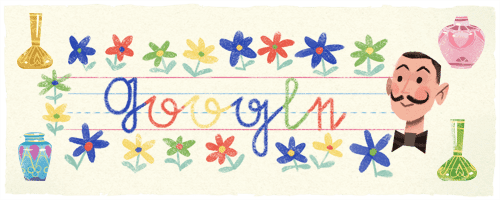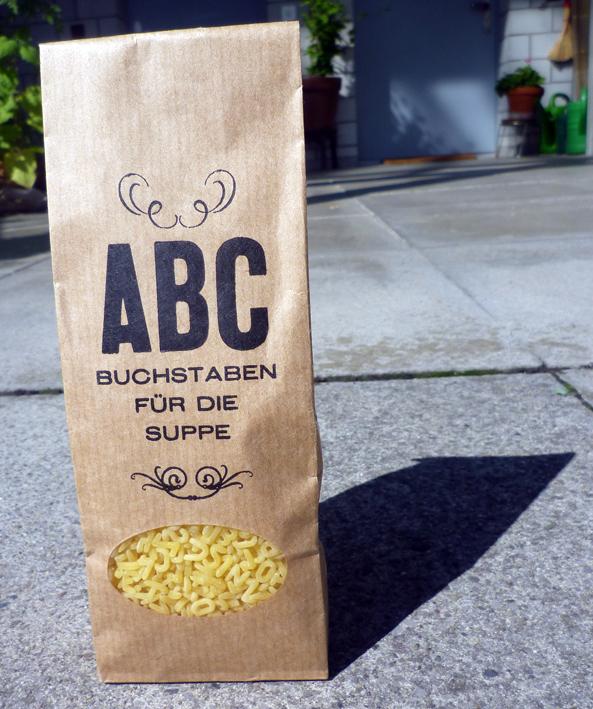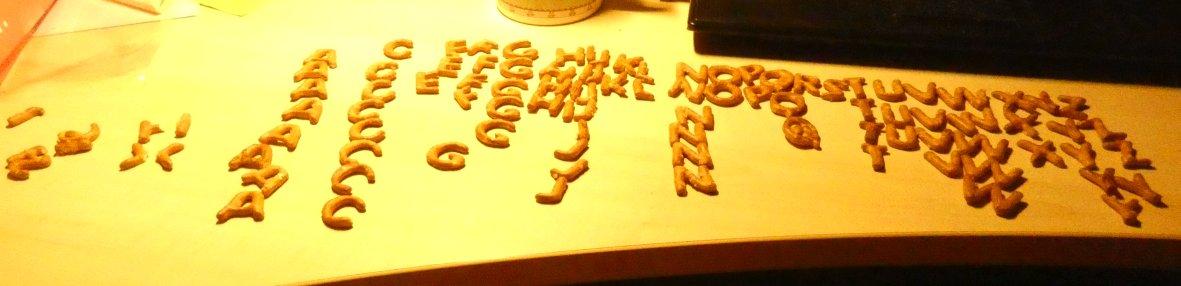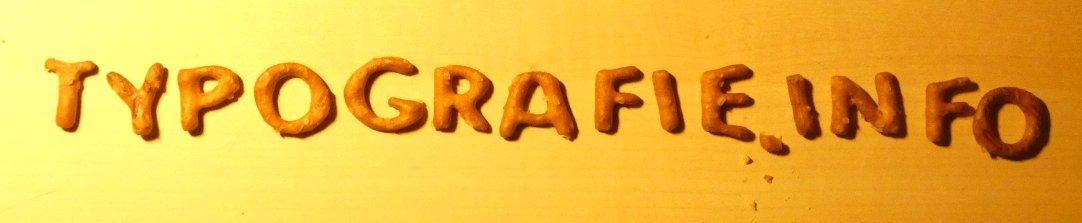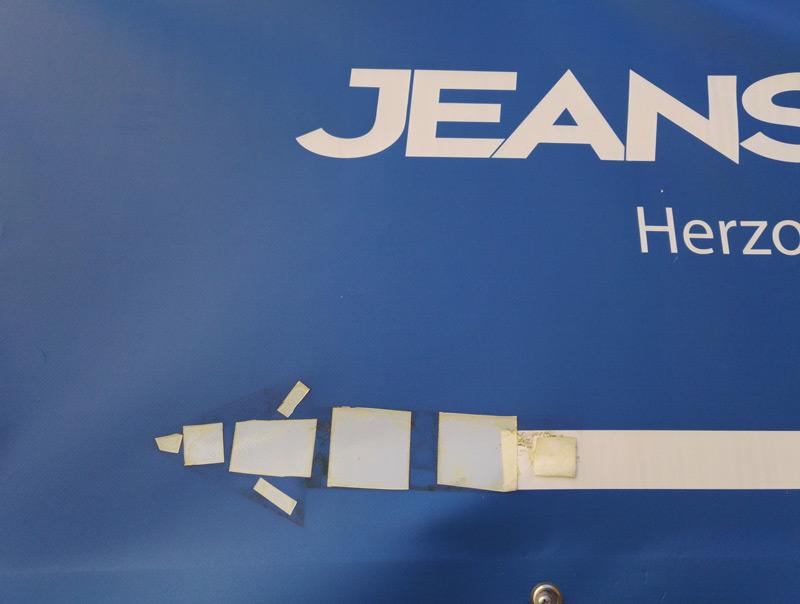
Eher sind die Kleinbuchstaben "ein Stockwerk" zu tief ... Bild zum Vergleich
<spekulation> Ursprünglich saßen sie korrekt auf der mittleren Linie. In letzter Minute fand aber jemand, dass der Schfriftzug irgendwie klein wirke. Weil der ursprüngliche Grafiker da aber schon Feierabend hatte und das Ding ins Netz musste, hat ein Praktikant sie halt rasch vergrößert, und zwar nach unten. Danach störte die frühere Grundlinie, da hat er sie eben gestrichelt. </spekulation)
Neon-Fraktur:
Oldenburg. #sapalot!
So ein schöner Pfeil ... liebevoll gestaltet mit nichts als einem Klebeband (und eventuell einer Schere). 😅
(gefunden in München auf einem Anhänger mit Plane)
*notier* _ONTAG _EI AL_I _ESCHWEREN!
Seit wann hat ALDI-Süd denn Buchstaben in der Knabberbox?
Wenn nix im Fernsehen kommt, habe ich nun Alternativen ...:ilovetype:
Nicht von Aldi sondern von der  Buchdruckerei Felder in Hergiswil:
Suppenbuchstaben in Handsatz-Verpackung